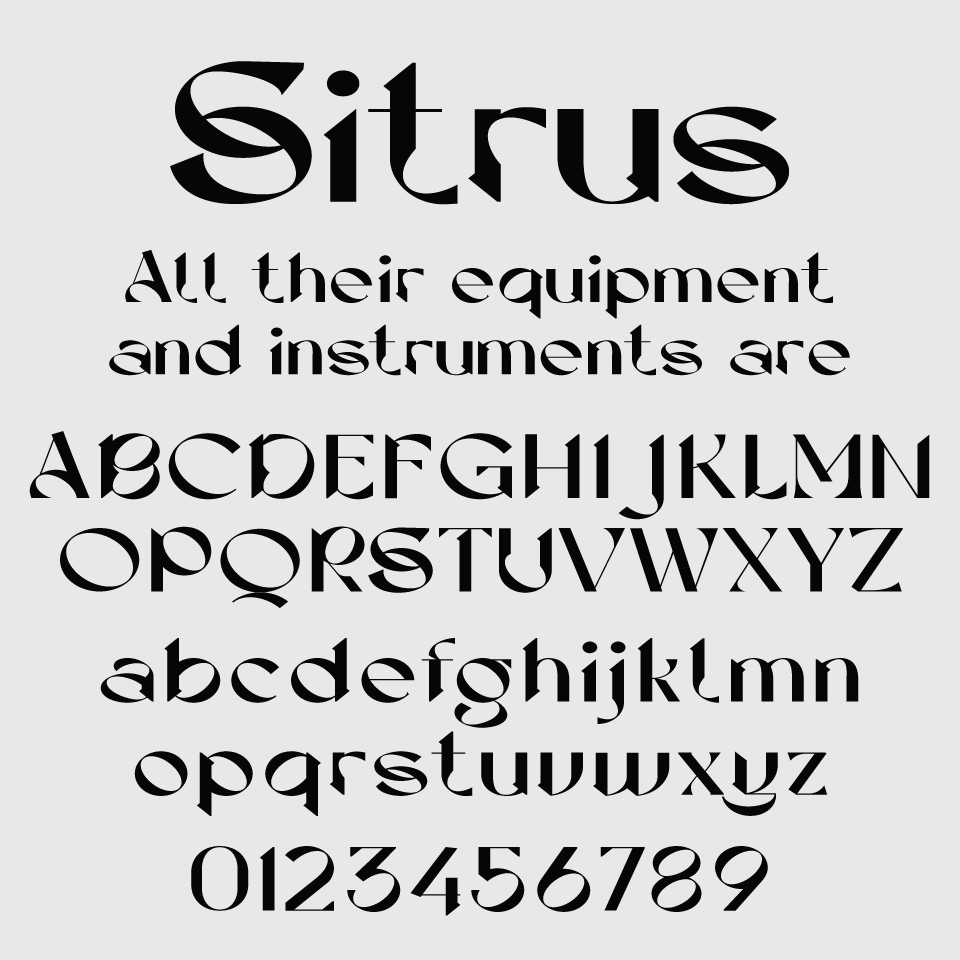
Dx Sitrusフォントは、楕円のようなフォルムと幾何学的なモダンさが融合したような独特のフォントです。
鋭くエッジのあるセリフや斜めのストロークが、ユニークな雰囲気を生み出しており、タイトルや装飾的なタイポグラフィとして映えます。
アール・デコやフューチャリスティックな印象も持ち合わせており、映画のロゴやゲームタイトルなど、非日常的なシーンでの使用にぴったりです。尖ったビジュアルを狙うときに、有機的かつスタイリッシュなアクセントを加えてくれるフォントです。